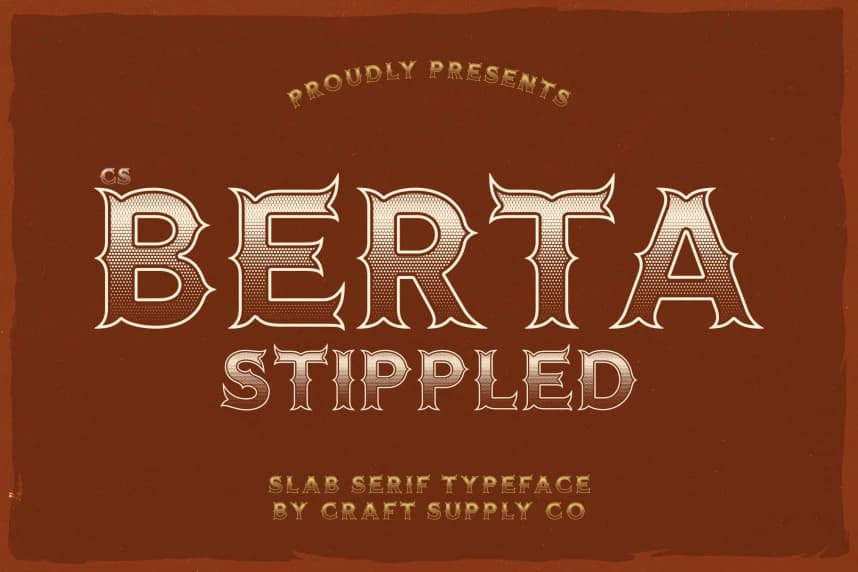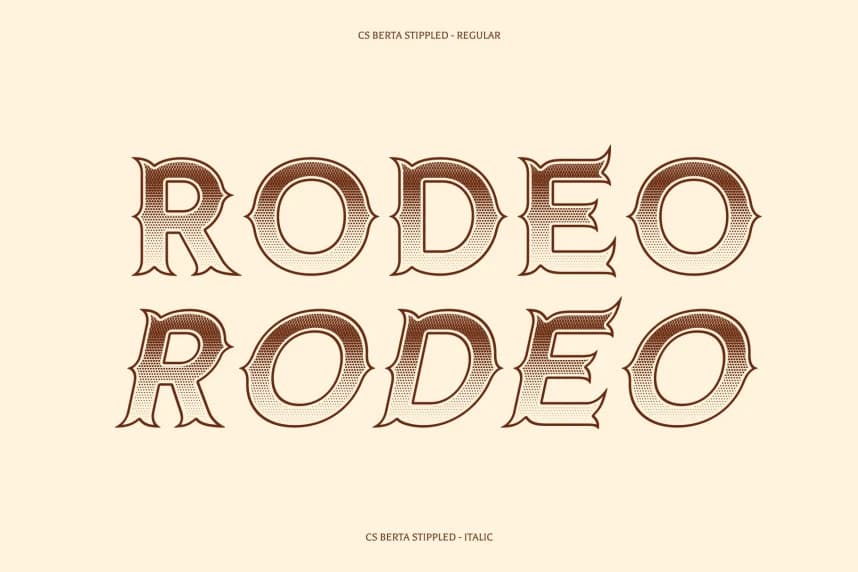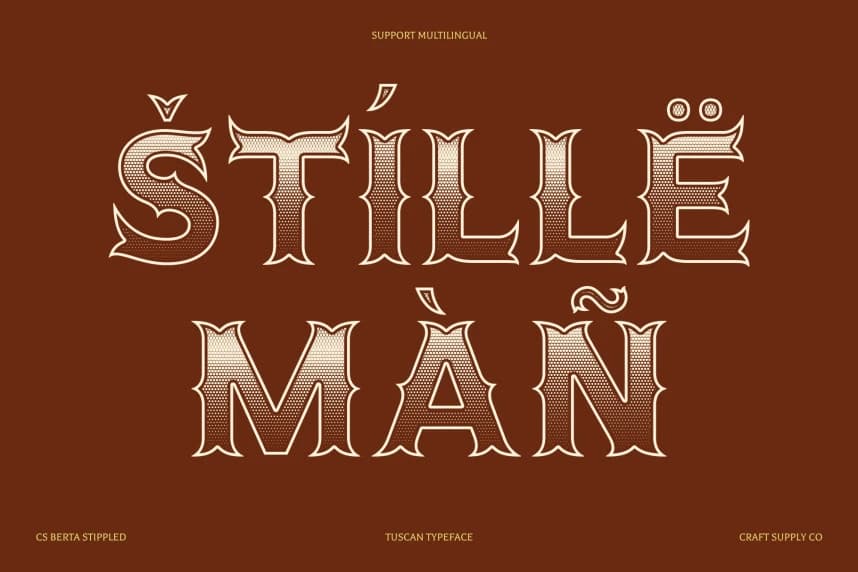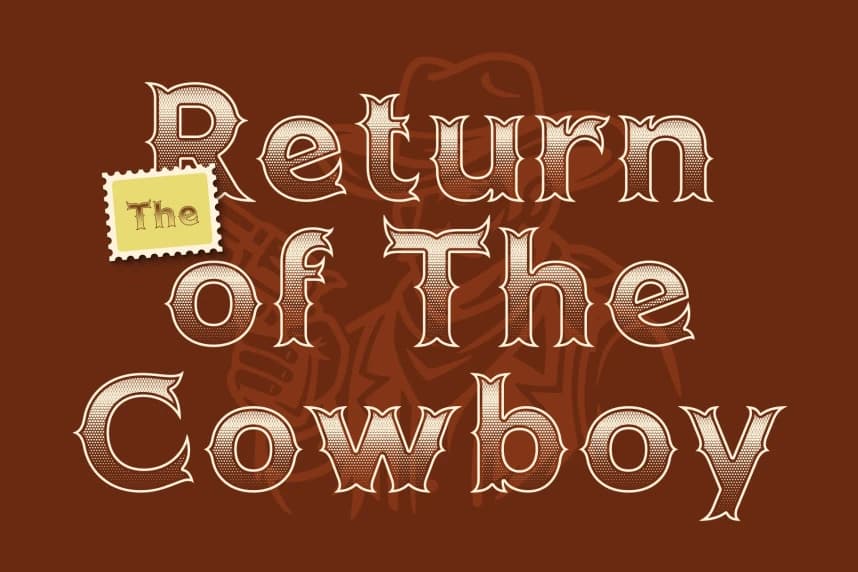
CS Berta Stippled Font
CS Berta Stippled Font – Tuscan Font: Kalın, Vintage ve Retro Serif Stilinde; Klasik Tuscan Tarzı, stipple dokulu derinlikle. Bu, geleneksel Tuscan tipografiden ilham alan çarpıcı bir gösterim serif yazı tipidir; şimdi yoğun stipple dokusuyla zenginleştirilmiştir.
CS Berta Stippled Font – Tuscan Font: Kalın, Vintage ve Retro Serif Stili. Benekli Derinliğe Sahip Klasik Tuscan Stili. Geleneksel Tuscan tipografisinden ilham alan çarpıcı bir gösteri serif yazı tipidir; şimdi yoğun benekli dokuyla zenginleştirilmiştir.
CS Berta Stippled
CS Berta Stippled Regular